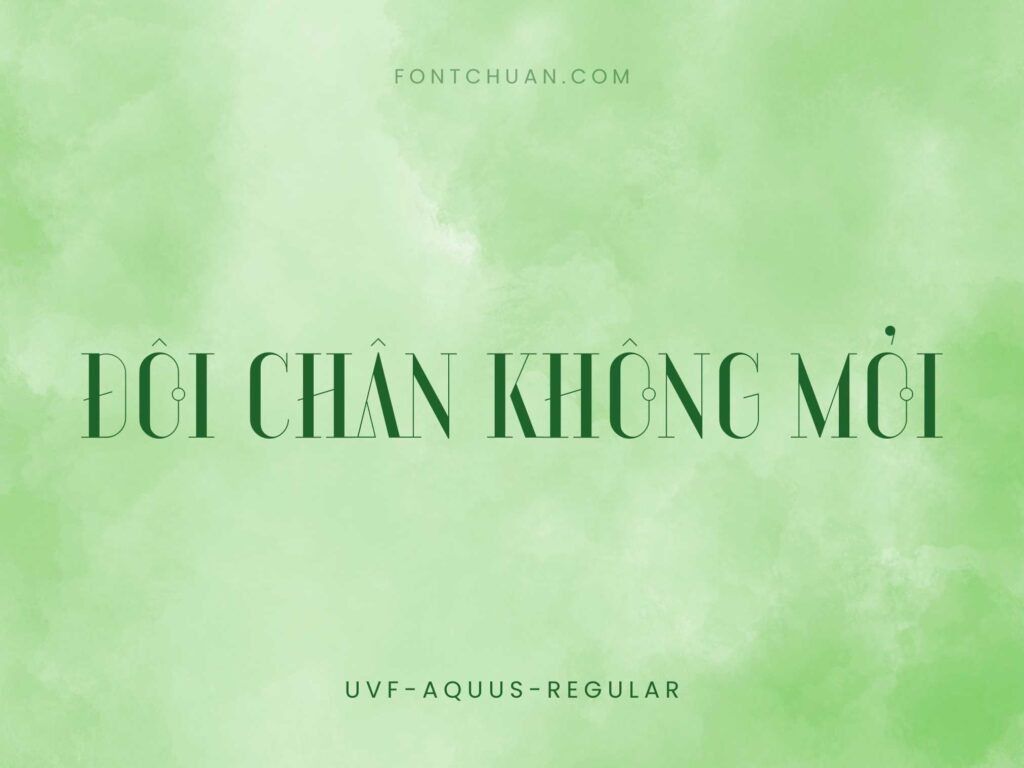
UVF AQUUS Regular là một font chữ sans-serif hiện đại, mang phong cách tối giản với các đường nét gọn gàng và tinh tế. Font này được thiết kế để tạo cảm giác chuyên nghiệp và rõ ràng, phù hợp cho các dự án như thiết kế logo, tiêu đề, bao bì sản phẩm và các ấn phẩm truyền thông. Với sự kết hợp giữa tính thẩm mỹ và khả năng ứng dụng cao, UVF AQUUS Regular giúp các thiết kế trở nên thanh lịch, dễ đọc và thu hút hơn.
Font này được sưu tầm và đăng bởi thành viên của Font Chuẩn. UVF AQUUS Regular hỗ trợ đầy đủ các ký tự tiếng Việt, mang lại trải nghiệm sử dụng hoàn chỉnh cho người dùng. Ngoài ra, font này còn hỗ trợ nhiều ngôn ngữ khác, mở rộng khả năng ứng dụng trong các thiết kế quốc tế.